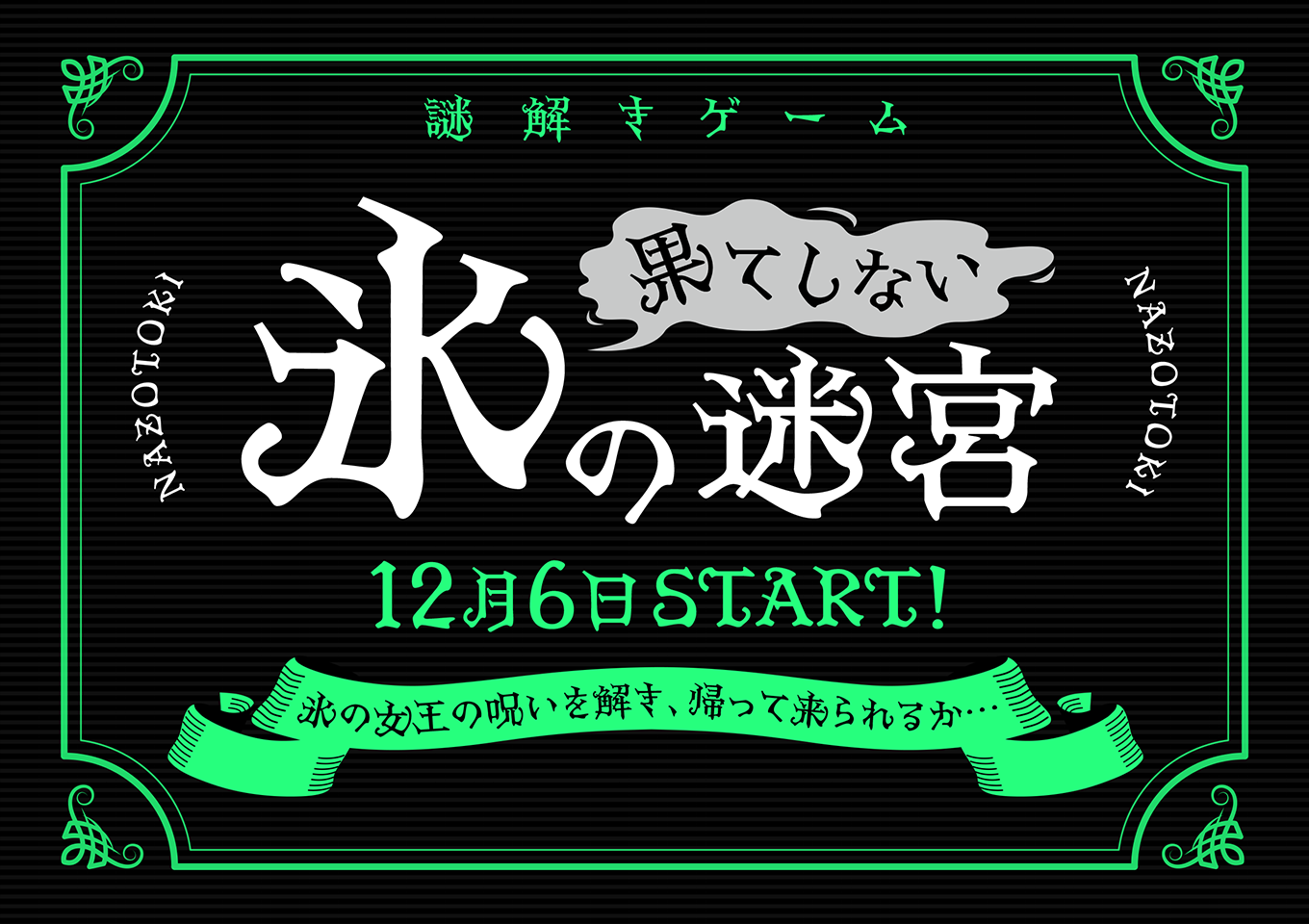
「月下香」は、独特のエレメントがミステリアスな雰囲気を醸し出すデザイン書体です。あえてアンバランスに設計された骨格と、つたのように上向きに伸びるハライや大きな打ち込みが非日常の世界観を演出し、見出しで強く目を惹く効果を発揮します。デフォルトのライニング数字のほかにオールドスタイル数字を搭載しており、OpenType機能を使って呼び出すことで、よりレトロな雰囲気を演出することもできます。